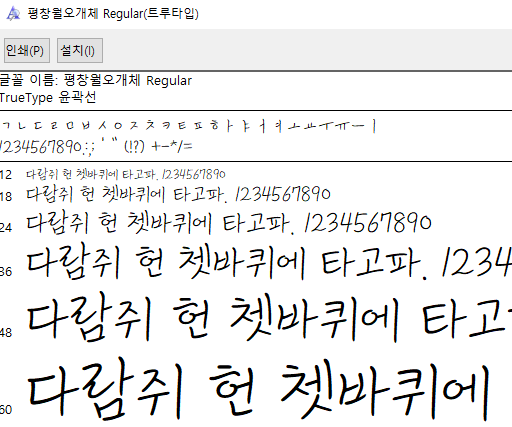
아래의 이미지에서 보듯이 평창월오개체 및 평창아름다름체는 자소의 크기와 형태가 다양한 전형적인 손글씨 형태로 평창군 주민들의 실제 손글씨를 폰트로 제작됐다.
해당 평창월오개체와 평창아름다름체는 한글 2780자에 영문 95자 그리고 KS 약물 95자로 구성되어 있는 평창군에서 제공하는 평창전용서체 중 하나이다. 참고로 평창전용서체는 평창월오개체와 평창아름다름체 이외에도 평창체, 평창평화체 등이 있는데, 모든 평창전용서체는 무료로 사용이 가능하다.